Nhiều designer gặp trở ngại khi tìm kiếm font chữ La Mã bị lỗi hiển thị dấu tiếng Việt hoặc đường chân chữ bị răng cưa khi phóng đại in ấn bằng khen. Những sai sót này làm giảm tính chuyên nghiệp của bộ nhận diện, gây mất thiện cảm trong mắt đối tác quan trọng. Xưởng In Viva cung cấp hệ thống kiểu chữ La Mã chuẩn sắc sảo, giúp bạn hoàn thiện các bản vẽ thiết kế chỉn chu.
Font chữ La Mã là gì và sức hút của phông chữ La Mã trong đồ họa?
Font chữ La Mã là nhóm phông chữ có nguồn gốc từ các bản khắc đá cổ đại của đế chế La Mã, đặc trưng bởi các đường chân chữ rõ rệt và cấu trúc ký tự vững chãi. Điểm nhấn của dòng phông này là sự kết hợp hài hòa giữa các nét thanh mảnh và nét đậm, mang lại cảm giác uy nghi, tin cậy và có bề dày lịch sử. Trong ngôn ngữ đồ họa đương đại, phông chữ La Mã được coi là tiêu chuẩn vàng cho những thiết kế yêu cầu tính chuẩn mực và sự trang trọng vượt thời gian.
05 Ứng dụng phổ biến của font chữ La Mã trong sản xuất và in ấn
Vẻ đẹp uy nghiêm và tính chuẩn mực của mẫu chữ có chân nâng tầm giá trị cho nhiều ấn phẩm truyền thông của đơn vị:
- Thiết kế bằng khen và chứng chỉ vinh danh: Font chữ La Mã là lựa chọn hàng đầu cho các mẫu bằng khen nhân viên xuất sắc hoặc chứng nhận đại lý. Những đường chân chữ sắc sảo mang lại cảm giác được trân trọng và tự hào cho người nhận hiện vật kỷ niệm, khẳng định uy tín của đơn vị cấp bằng.
- Sản xuất bao bì yến sào và dược liệu cao cấp: Sử dụng font La Mã cho tiêu đề trên các dòng hộp giấy Ivory hay hộp cứng đựng sâm quý. Những nét chữ vững chãi tạo cảm giác sản phẩm có nguồn gốc tin cậy, chất lượng vượt trội, dễ dàng ghi điểm với phân khúc khách hàng thượng lưu.
- Gia công in UV trên các sản phẩm văn phòng: Logo và slogan dùng font số La Mã đẹp được in trên bình giữ nhiệt kim loại hoặc sổ tay da. Độ sắc sảo của tệp vector giúp các đường chân chữ hiển thị rõ nét trên các bề mặt sẫm màu, tạo vẻ ngoài bền bỉ theo dòng thời gian.
- Trang trí bộ ấm chén sứ tri ân đối tác: Hình ảnh chữ nghệ thuật dùng phông chữ La Mã in nung trên men sứ trắng mang lại vẻ đẹp nhã nhặn, cổ kính cho các bộ trà sứ, là hiện vật trưng bày tinh tế cho các buổi lễ ký kết hợp tác quan trọng.
- Sản xuất đồng hồ và kỷ niệm chương: Font chữ số La Mã thường xuất hiện trên mặt đồng hồ treo tường hoặc kỷ niệm chương pha lê. Sự kết hợp giữa con số cổ điển và kỹ thuật khắc laser tinh xảo giúp sản phẩm đạt độ hoàn thiện cao, thể hiện gu thẩm mỹ sang trọng của doanh nghiệp.
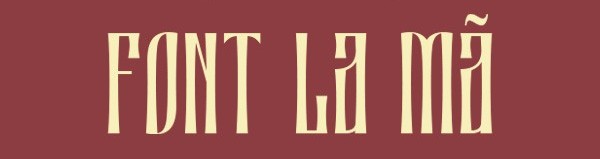
04 Lưu ý kỹ thuật khi sử dụng font chữ La Mã đẹp in ấn thực tế
Để hệ thống ký tự có chân hiển thị sống động và bền màu trên các thành phẩm thực tế như bao bì giấy hay hiện vật tri ân đối tác, designer cần chú trọng:
- Kiểm soát khoảng cách giữa các ký tự (Kerning): Font La Mã có các đường chân chữ vươn dài. Designer nên điều chỉnh khoảng hở hợp lý để khi in lụa trên túi vải hoặc các bề mặt nhám, các chân chữ không bị dính vào nhau gây mất dáng chữ hoặc nhòe nét mực.
- Tối ưu đường Path cho gia công bế nổi: Bước này quan trọng khi sản xuất nắp hộp cứng dập nổi logo doanh nghiệp. Kỹ thuật viên cần làm mượt từng điểm neo bo tròn trong file vector giúp khuôn bế thực hiện chính xác, tạo hiệu ứng nổi khối rõ nét cho các chi tiết chân chữ Serif mà không làm rách giấy.
- Thiết lập hệ màu CMYK cho tông màu trầm ấm: Kiểu chữ này thường đi cùng sắc đỏ chu sa, xanh rêu hoặc vàng đồng. Designer cần hiệu chỉnh hệ màu CMYK chuẩn in ấn tại xưởng và yêu cầu mẫu thử để đảm bảo màu chữ sau in không bị ám xám hay mất sắc độ so với bản vẽ máy tính.
- Bảo toàn tỉ lệ cấu trúc chữ: Khi thu phóng font chữ số La Mã đẹp, designer phải giữ đúng tỉ lệ gốc của bộ chữ. Việc kéo giãn quá mức sẽ làm hỏng tính cân đối của các nét thanh đậm, làm mất đi vẻ đẹp sang trọng và sự uy nghiêm vốn có của phông chữ cổ điển.